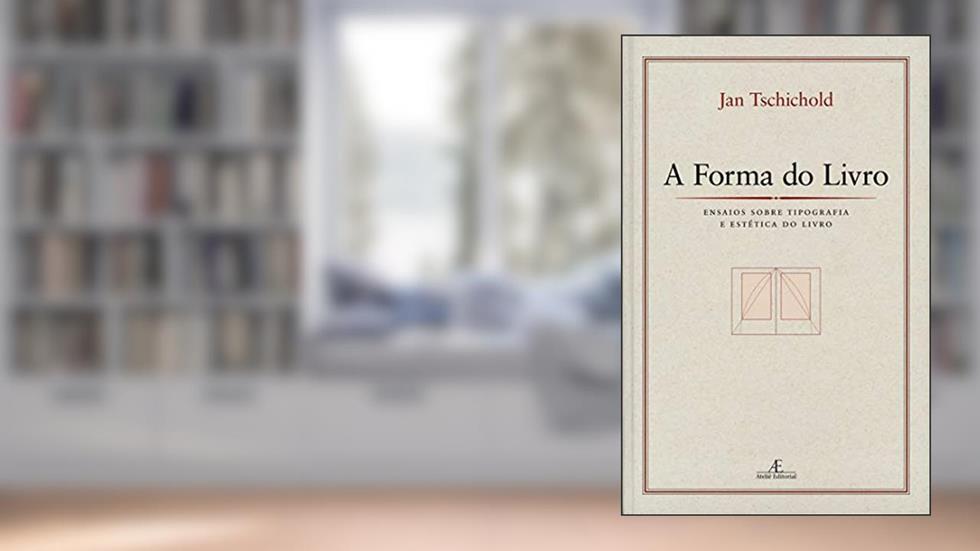
A Forma do Livro: Ensaios sobre Tipografia e Estética do Livro, do autor Jan Tschichold
A Forma do Livro
Ensaios sobre Tipografia e Estética do Livro
Jan Tschichold
Ler A Forma do Livro: Ensaios sobre Tipografia e Estética do Livro, do autor Jan Tschichold
Em cada folha de A Forma do Livro: Ensaios sobre Tipografia e Estética do Livro, de Jan Tschichold, respira-se a essência do design gráfico em sua forma mais pura e estimulante. Esta não é apenas uma obra; é um manifesto que transcende o papel, cada palavra e cada página convergem para uma reflexão intensa sobre a maneira como interagimos com os livros e a estética que os envolve. Tschichold, um pioneiro no design tipográfico, se torna nosso guia nesta jornada, desmistificando o que significa "ler" em um mundo onde a forma e a função muitas vezes se encontram em dança.
Você já se perguntou por que um livro te toca mais que outro? É a mágica da tipografia. Tschichold não poupa esforços em mostrar que a escolha da fonte, o espaçamento e a disposição do texto não são mera estética: são elementos que moldam a experiência do leitor. Em suas páginas, ele nos obriga a enxergar a importância do design na leitura. Você verá que cada letra é uma nota musical, cada parágrafo, uma sinfonia que guia a mente e o coração do leitor em uma jornada indescritível.
A obra também faz uma imersão no contexto histórico da época, revelando como a tipografia evoluiu e influenciou movimentos sociais e culturais. Você ficará fascinado ao descobrir que a forma como os livros foram projetados não é só uma questão de beleza, mas tem implicações profundas nas ideias que propagamos e nas narrativas que contamos. Em tempos onde a informação é consumida rapidamente, Tschichold resgata a importância de pausar, de contemplar e de nos deixarmos impactar pela arte que é a leitura.
Os leitores se dividem entre aqueles que o consideram um verdadeiro mestre da estética e os que veem suas opiniões como arrojadas demais. Alguns elogiam a habilidade de Tschichold em conectar a teoria à prática, enquanto outros questionam se ele não se perdeu em sua paixão pela forma. Essa dicotomia faz parte do encanto da obra: provoca debate, reflexão e, acima de tudo, instiga a busca pela perfeição em cada livro que passa pelas nossas mãos.
Se você é um amante da literatura, um designer gráfico ou alguém que simplesmente aprecia a beleza do impresso, a leitura de A Forma do Livro promete ser transformadora. Não se trata apenas de apreciar o produto final, mas de entender a mensagem que cada página carrega e o impacto que a forma tem na nossa percepção. Tschichold nos ensina que o ato de ler pode ser uma experiência transcendental, quando entendemos e valorizamos a beleza do que há por trás do que seguramos em nossas mãos.
Deixe-se envolver pelas páginas deste ensaio e descubra um universo que vai muito além das palavras. Cada sessão é um convite à contemplação, um chamado para que você não apenas leia, mas viva o livro em sua totalidade. Não tenha medo de se perder nesse labirinto de letras e formas. Afinal, a verdadeira literatura é aquela que nos toca profundamente, nos desarma e nos transforma.